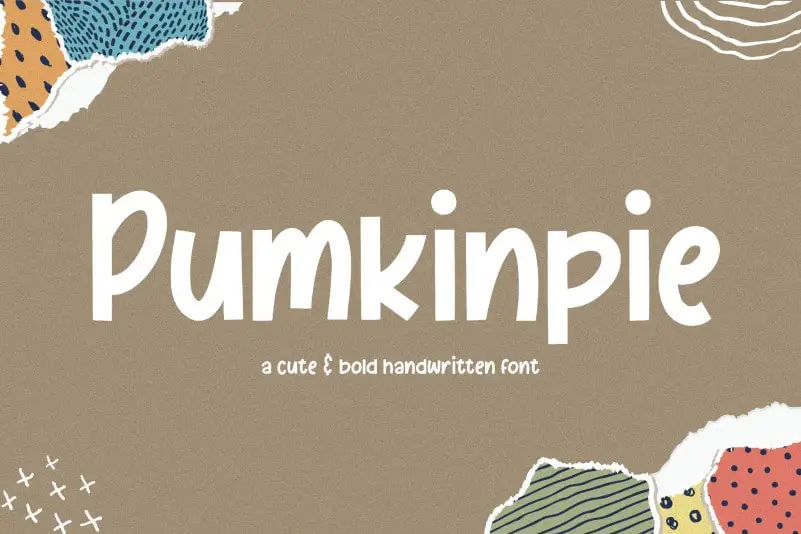
Pumkinpie Cute & Bold Handwritten Font – Download Grátis
A fonte Pumkinpie Cute & Bold Handwritten é perfeita para quem busca uma opção divertida e única para enriquecer a identidade visual de suas criações digitais. Ideal para aplicar em embalagens de produtos, projetos de marca, revistas, postagens nas redes sociais, cartões de casamento ou simplesmente quando se deseja destacar os elementos da superfície com letras coloridas e elegantes. Com sua escrita afetuada e cheia de personalidade, a Pumkinpie oferece uma maneira criativa de expressar seu ponto de vista. Suas linhas dinâmicas e traços suaves garantem que a letra se destaque harmoniosamente em qualquer contexto visual, seja grande ou pequeno. Para designers, especialistas em marketing e criativos de todos os tipos, essa fonte é uma ferramenta valiosa para criar mensagens memoráveis e impactantes. Seja com letras grandes nas embalagens ou detalhes sutis nos posts da web, Pumkinpie entrega o toque final perfeito ao seu trabalho.